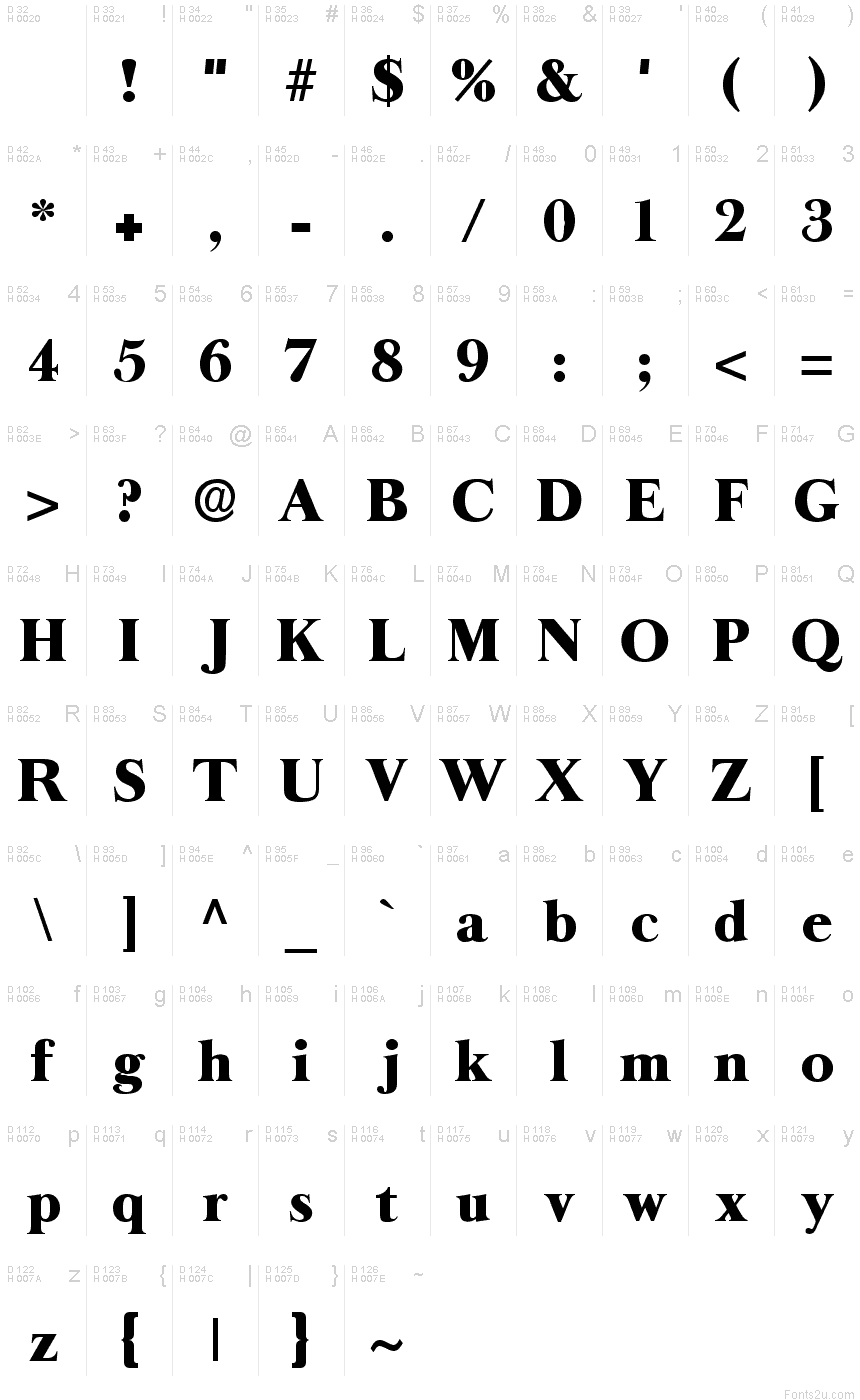
Long Island to darmowy krój szeryfowy z delikatnymi szeryfami i stabilną, kompaktową budową. Powtarzające się krzywizny nadają mu spokojny rytm, a całość sprawia wrażenie powściągliwej, lecz nie surowej.
Long Island doskonale sprawdzi się na okładkach książek, w tytułach magazynów, menu restauracyjnych, na opakowaniach i zaproszeniach – jej szeryfowa struktura jest formalna, ale nie sztywna czy przesadzona. Świetnie nadaje się też do logotypów i krótkich cytatów, gdzie klasyczny napis lub linia redakcyjna wymaga niezawodnego kroju z miękko wykończonymi detalami i wyraźnym, równym rytmem.